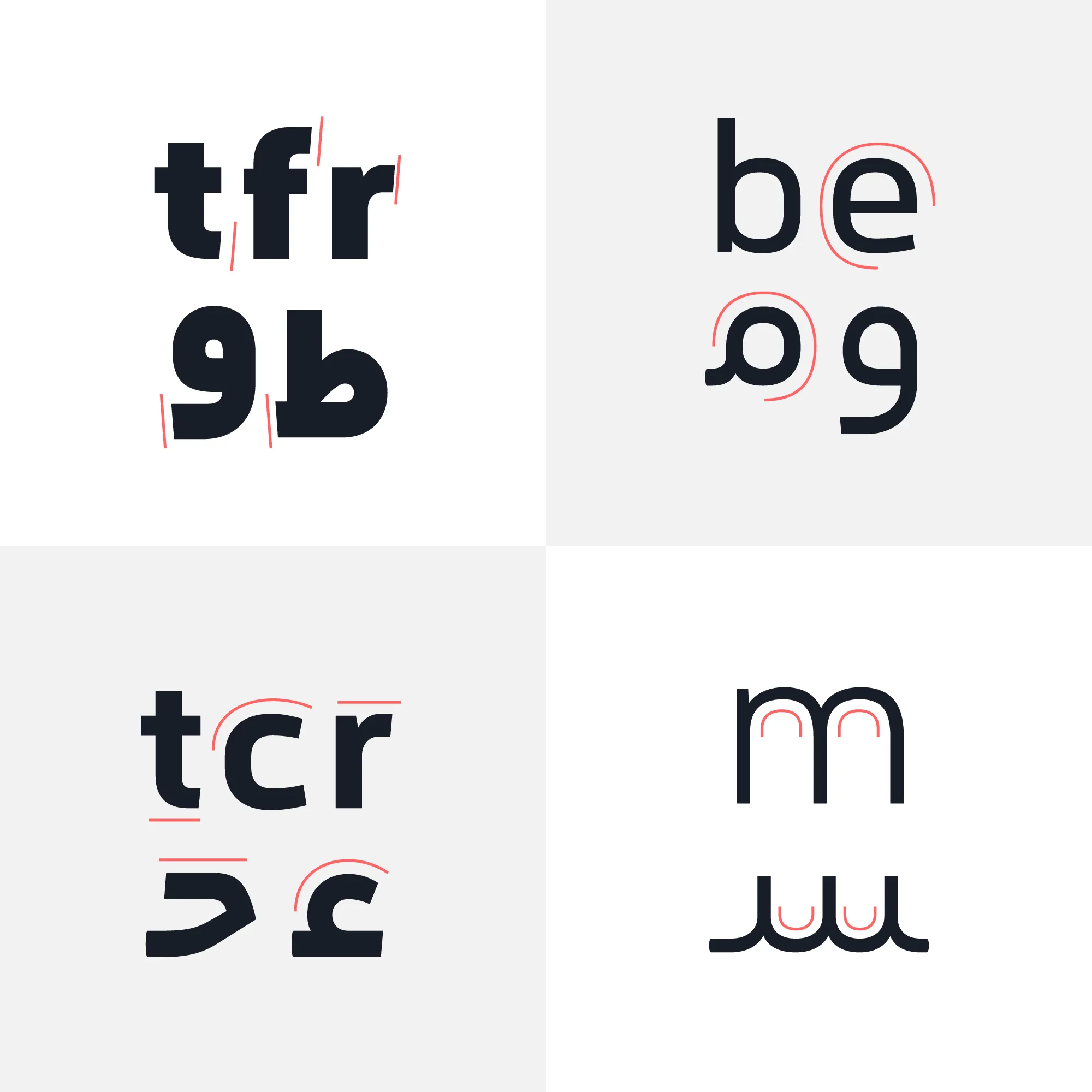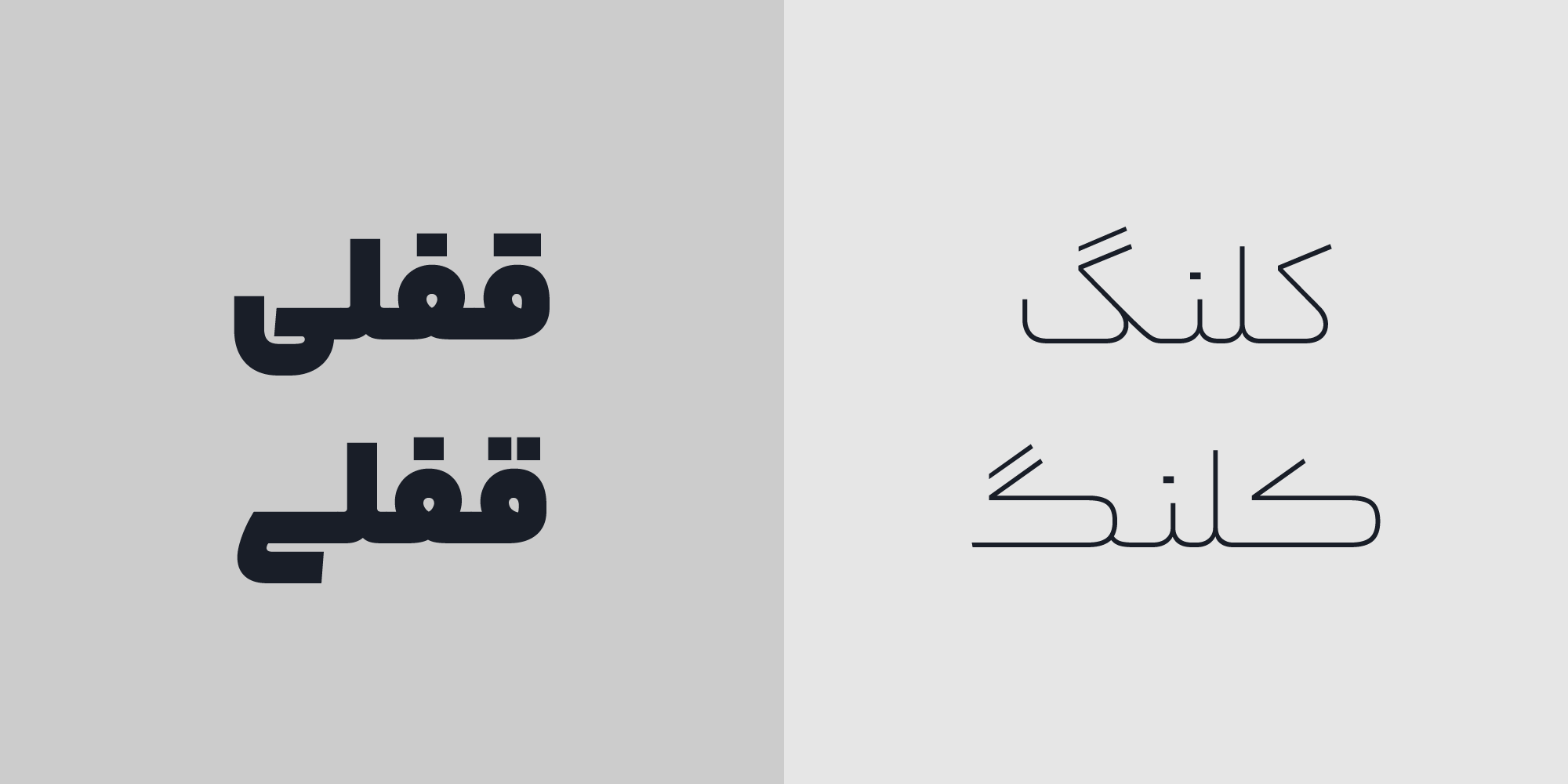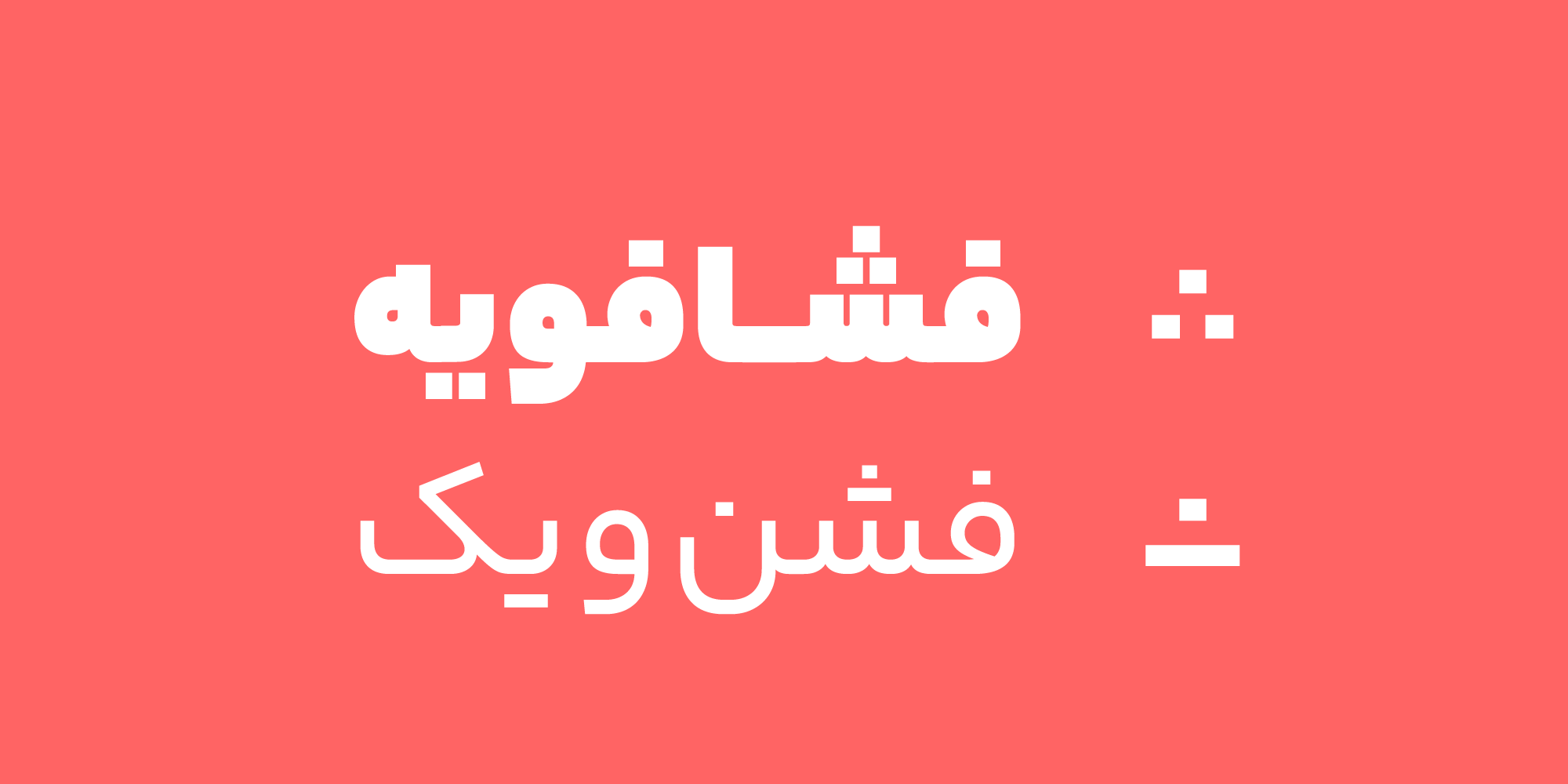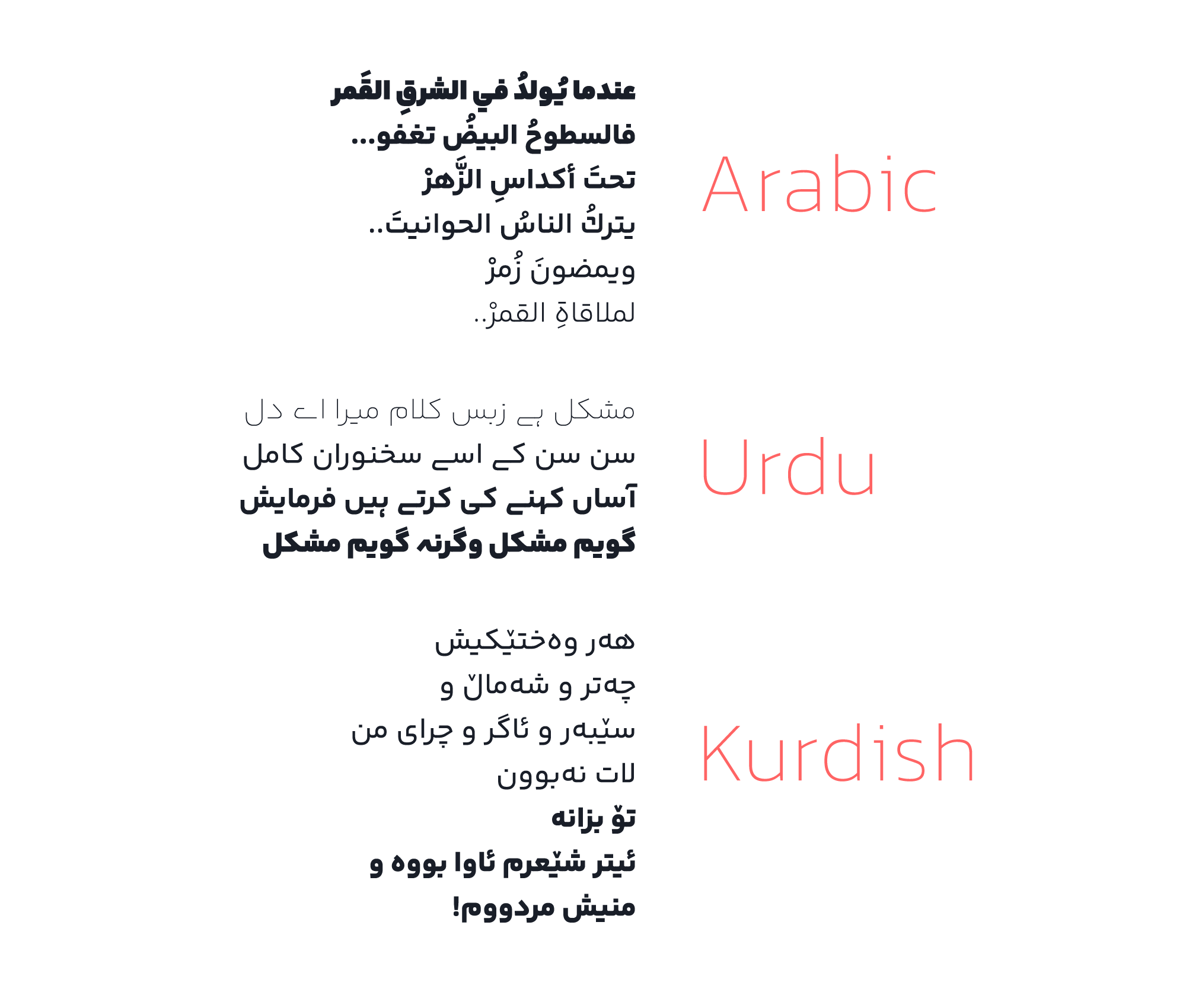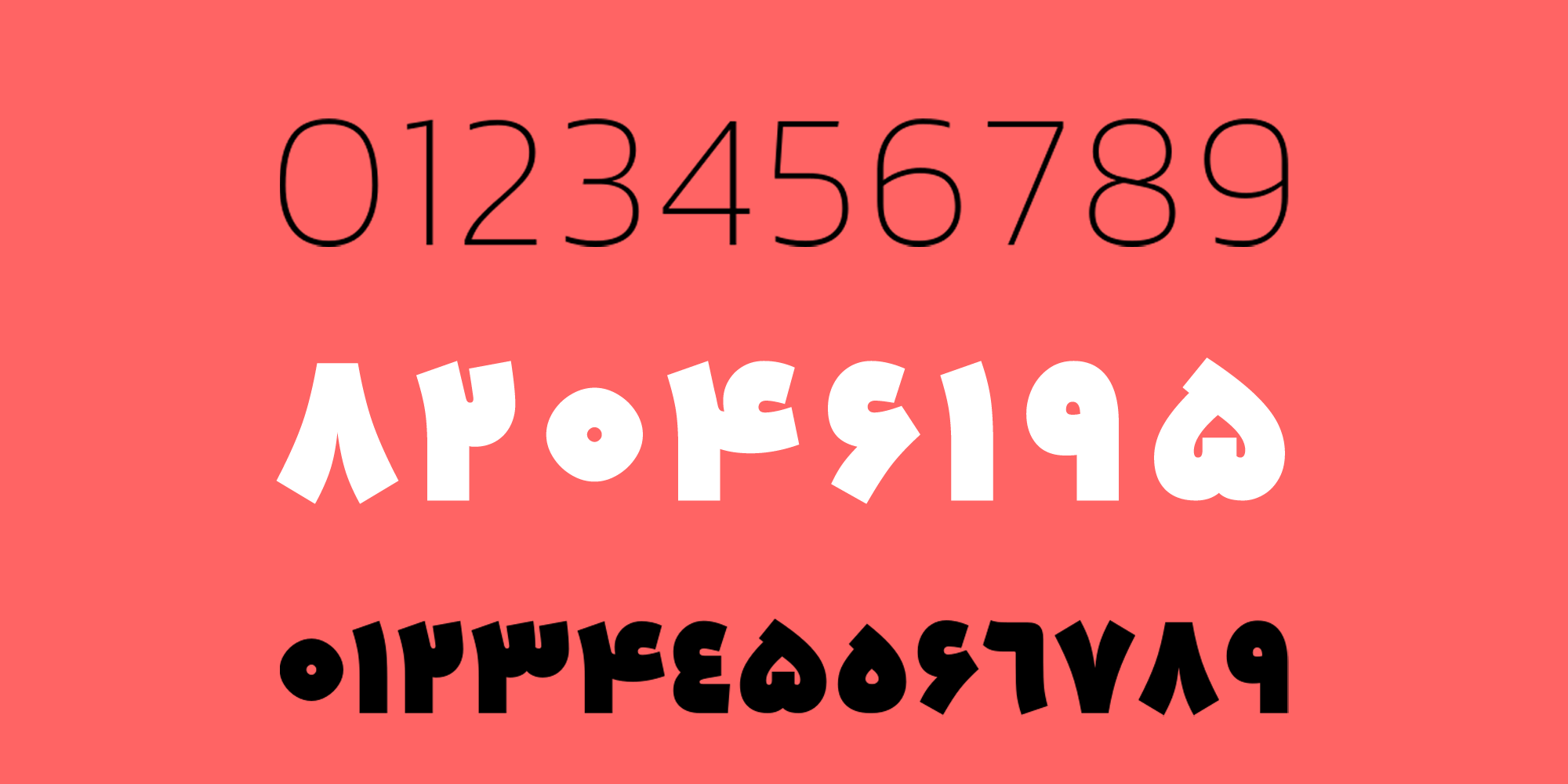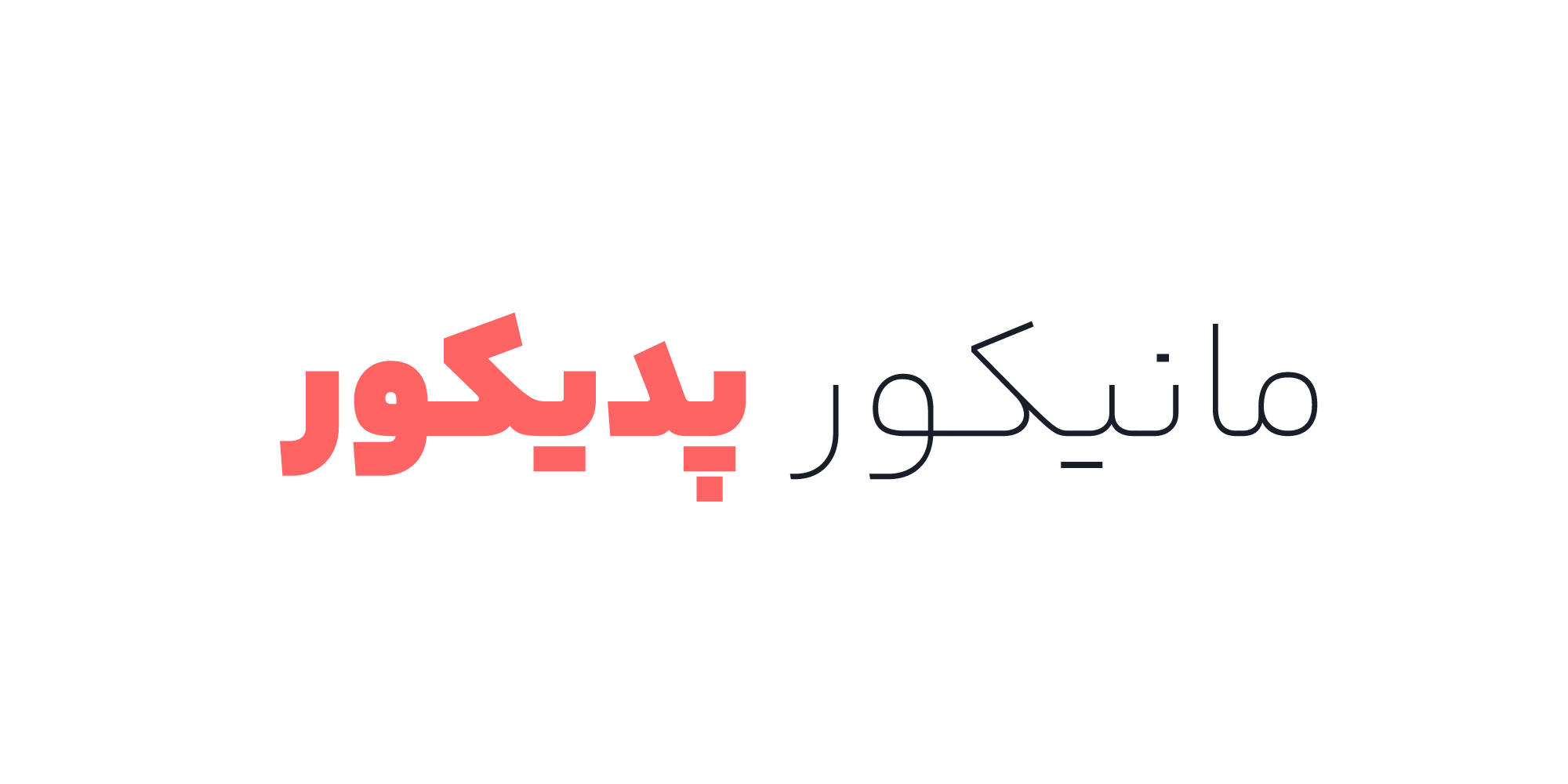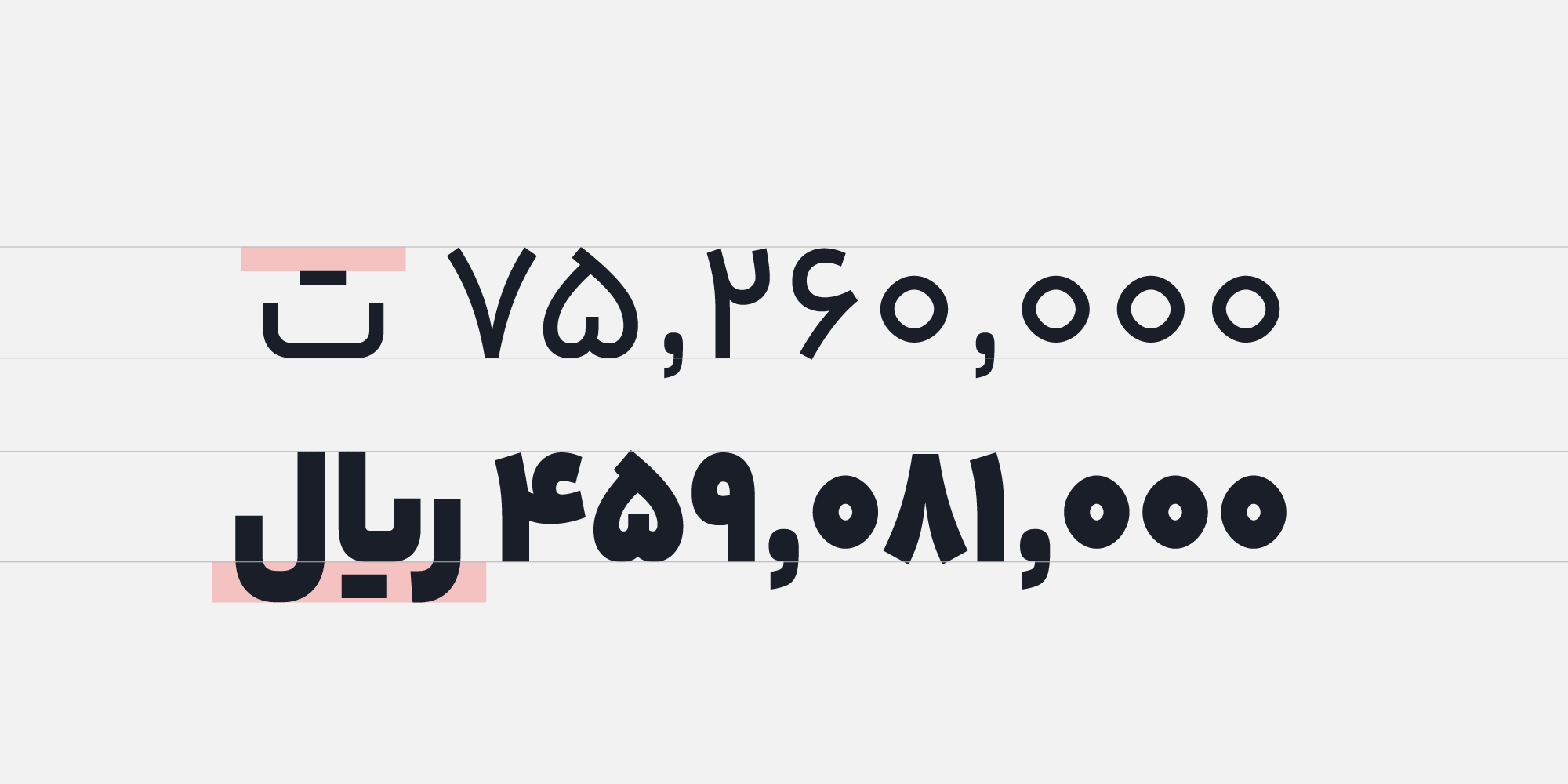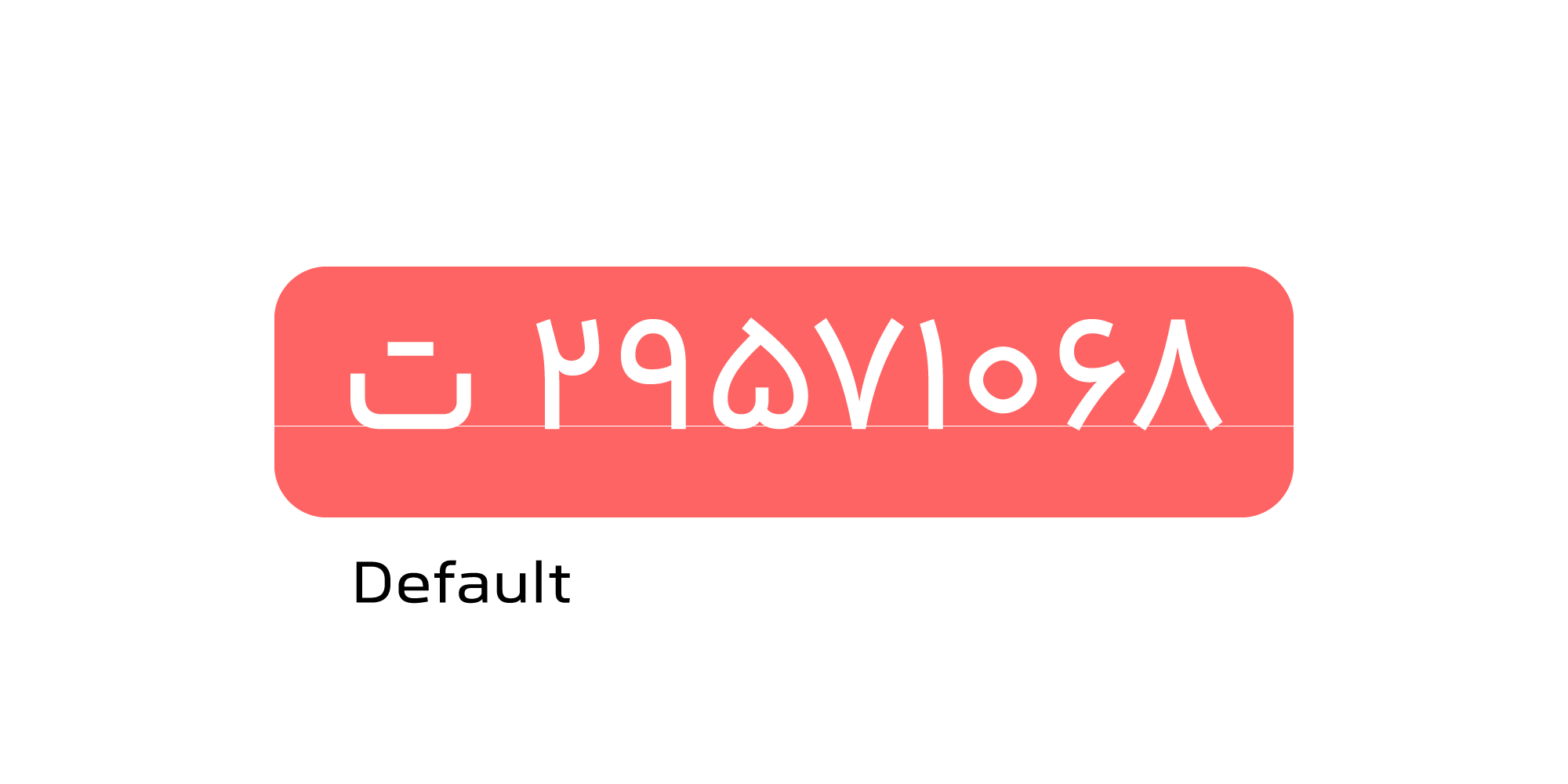
فونت یکان بخ (YekanBakh)
فونت یکان بخ (به انگلیسی: YekanBakh) در گروه فونت‌های هندسی قرار دارد که بر پایه خط نسخ توسط رضا بختیاری فرد طراحی شده است. این قلم را می‌توان یک بازطراحی از فونت یکان درنظر گرفت که توسط مسعود سپهر در سال ۱۳۵۹ طراحی شده است.
این فونت که دارای طراحی مونولاین (ضخامت یکسان و خطی در سرتاسر حروف) ساخته شده، دارای منحنی و زاویه قلم خاصی است. در نگاه اول این فونت کاملا مونولاین دیده می‌شود که نتیجه خطای دید به دلیل وجود همین منحنی‌هاست؛ در حالی که فونت تا حدودی در برخی بخش‌ها دارای ضخامت کمتر است.
در ادامه این نوشته از سایت فونتچی به نقد و بررسی کامل فونت یکان بخ می‌پردازیم؛ فونتی بر پایه خط نسخ که یک بازطراحی کلی از خانواده یکان بوده و با پشتیبانی از نسخه وریبل، امکانات و قابلیت‌های ویژه‌ای را برای استفاده در فضای دیجیتال؛ خصوصا شبکه‌های اجتماعی در اختیار ما قرار خواهد داد.
این فونت برای استفاده در فضاهای پیکسلی به‌ویژه صنعت چاپ و مطبوعات بهترین خروجی و عملکرد را از خود نشان خواهد داد.
فونت یکان‌بخ را می‌توان از نظر پشتیبانی زبان جزو غنی‌ترین قلم‌ها دسته‌بندی کرد. خصوصا که از نسخه ۳.۱ این فونت بسیاری از زبان‌های محلی که زیرمجموعه فارسی و عربی بوده و در جای‌جای کشورمان قومیت‌های مختلفی با این زبان‌ها زندگی می‌کنند افزوده شده است که همین مسئله این قلم را به یکی از پربارترین فونت‌های فارسی تبدیل کرده است.
در طراحی یکان‌بخ از فرم‌های هندسی کمک گرفتم، اما خود را به استفاده از آن فرم‌ها محدود نکردم و کاراکترها به‌طور کامل با فرم‌های هندسی منطبق نیستند. دلیل این کار حفظ خوانایی و در نظر گرفتن خطای دید در طراحی بود. هم‌چنین فرم‌های هندسی باعث می‌شوند حروف شخصیتی سرد و ماشینی به‌خود بگیرند؛ به‌ویژه در رسم‌الخط عربی که چندان با فرم‌های هندسی میانه‌ای ندارند.
رضا بختیاری فرد؛ طراح قلم یکان‌بخ.
در این قلم نقاط به صورت چسبان طراحی شده و با فاصله جدا از هم نیستند که خود دلیلی برای خاص بودن این فونت برای استفاده در فضای تبلیغات و صنعت چاپ است.
سبک طراحی و وزن فونت یکان بخ
قلم هندسی یکان بخ یک فونت مناسب برای استفاده در عناوین و متون است که از ۸ وزن مختلف نازک تا خیلی سیاه را پشتیبانی کرده و در این بین نسخه وریبل متغیر که همه وزن‌های ۸ گانه را در قالب یک فایل در اختیارتان قرار می‌دهد را پشتیبانی می‌کند.
پشتیبانی از ۵ زبان متنوع
فونت فارسی یکان بخ محدود به این زبان نبوده و جزو قلم‌هایی است که پشتیبانی چند زبانه را دارند. این قلم از زبان‌های عربی، اردو، کردی و ترکی که از رسم خط فارسی استفاده می‌کنند پشتیبانی کاملی دارد که شامل تمامی حروف، اعراب و کاراکترهای خاص و تزئینی است.
تفاوت‌هایی هم که در هر زبان برای حروف وجود دارد، از جمله در زبان عربی برای حروفی مثل «ک، ی، ه، ؤ، ئ» یا در زبان اردو که حروف «ی» پایانانی متفاوت هستند پیاده سازی شده است.
برای نسخه انگلیسی این فونت تا پیش از نسخه ۳ از قلم Kanit استفاده میشد که طراحی بسیار نزدیکی به قلم یکان بخ داشت؛ اما از نسخه سون حروف لاتین در این قلم نیز به‌منظور هم‌آهنگ‌سازی با نسخه فارسی، با همکاری ماهان جعفرزاده صاحب گلیف اختصاصی خود شده‌اند که در تصویر زیر نمونه‌ای از آن را مشاهده می‌کنید.
در زبان کردی نیز انواع کاراکترهای تزئینی که روی حروف استفاده می‌شود تعبیه شده که در تصاویر بالا برای هر زبان نمونه‌ای از آن را می‌بینید. همچنین از نسخه ۳.۱ این فونت، زبان‌های لری، ترکی، کردی، اردو، جاوی، پگون، بلوچی، پشتو، سندی، کشمیری، تاجیکی، سواحلی، قرقیز، اویغور، قزاق، روهینگیا و ولوفال که زیرمجموعه‌ای از زبان فارسی و عربی هستند افزوده شده است.
فونت وریبل یکان بخ با متغیرهای چندگانه
فونت یکان بخ وریبل ویژگی دیگر این قلم است که متشکل از یک فونت با حجم‌کم، اما شامل همه وزن‌ها و امکانات این مجموعه فونت است که در قالب یک فایل در اختیار شما قرار می‌گیرد. از نسخه متغیر این قلم می‌توانید در سایت و حتی سیستم عامل استفاده کنید که همه وزن‌های نازک تا خیلی سیاه را درون یک فایل در خود جای داده است.
می‌توانید با تنظیم مقدار بین ۱۰۰ که معرف وزن Thin تا مقدار ۹۰۰ که معرف وزن ExtraBlack این قلم است را در تمامی نرم‌افزارهای گرافیکی از طریق تنظیمات open type مشخص کنید. برای استفاده در وب فونت هم کافی است از مقدار font-weight در CSS استفاده کرده و وزن دلخواه را انتخاب کنید.
ویژگی دیگر نسخه وریبل یکان بخ امکان تعیین شکل نقطه‌ها است که می‌توانید با استفاده از متغیر Dots نقاط را به صورت معمولی جداگانه یا چسبیده به هم مشابه با تصویر بالا در اختیار داشته باشید.
اما در نسخه ۳ فونت یکان بخ شاهد تحول گسترده‌ای در نسخه وریبل این قلم هستیم که علاوه بر متغیرهای بالا، متغیر جدید به‌منظور ایجاد کشیدگی عرضی نیز ایجاد شده است که در تصویر بالا نمونه آن‌را مشاهده می‌کنید که در تمامی وزن‌ها امکان تغییر Expand را به شما خواهد داد.